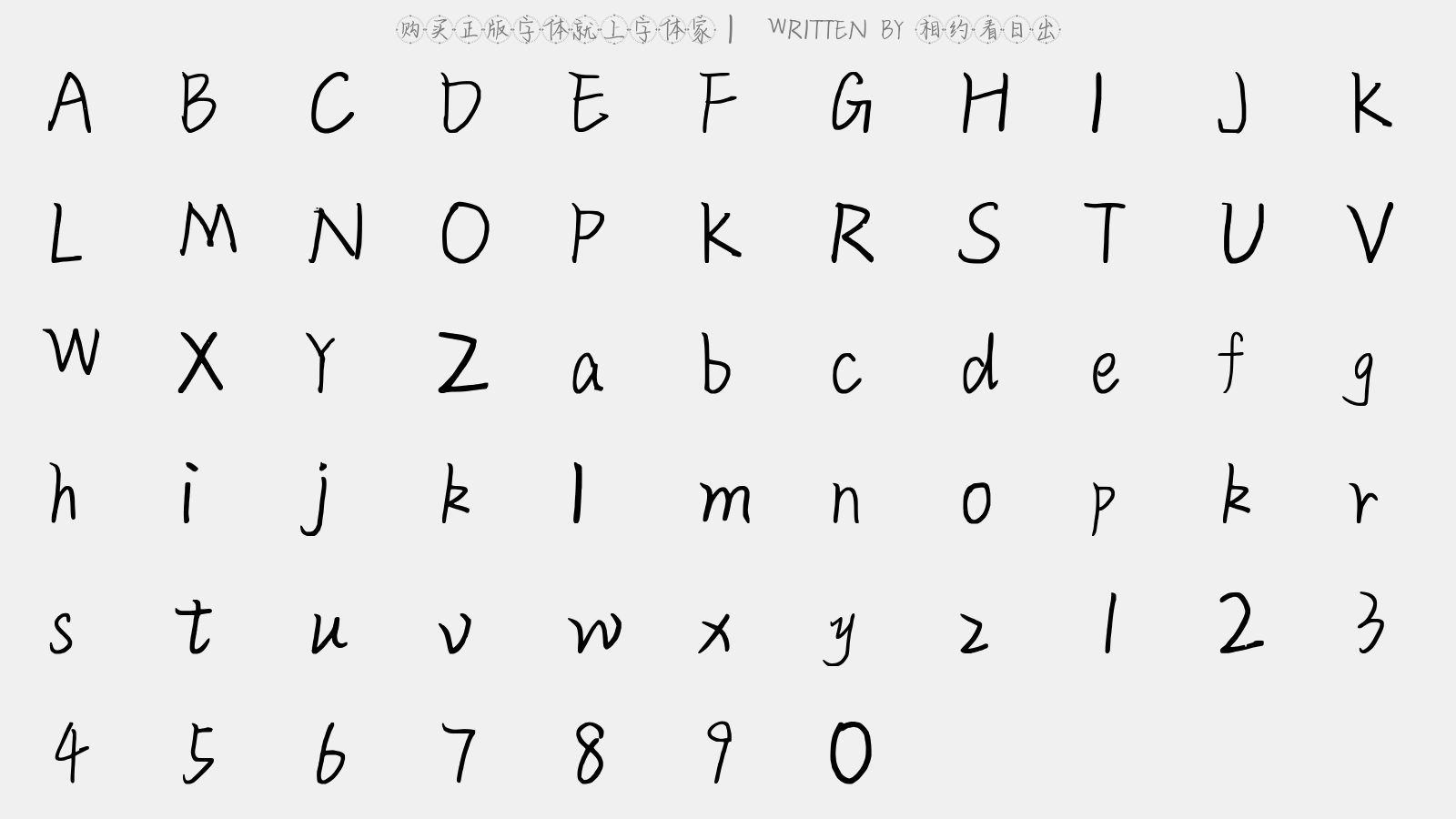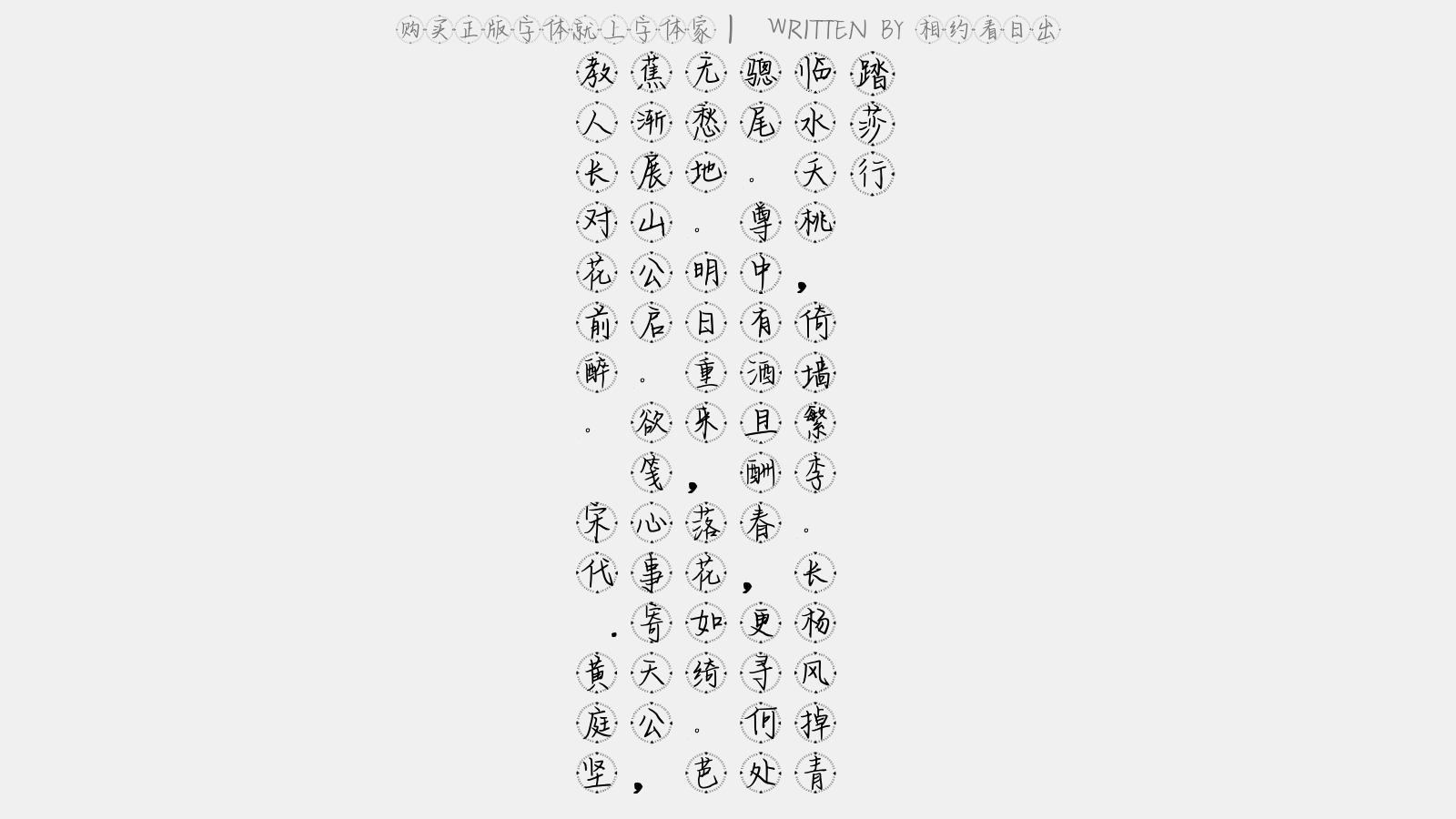
相约看日出
字体作者:红豆字库
字体名称:相约看日出
字体家族:红豆字库
书体类型:手写体、印刷体
字体公司:青岛绿光数字科技有限公司
相约看日出
相约看日出是一款非常不错的艺术字体,由红豆字库出品,个性醒目,具有强烈的视觉冲击力,适应于报纸和杂志和书籍中常用字体, 海报、个性促进品牌标志设计、字体设计、等环境使用,欢迎喜欢的朋友前来字体家下载使用。